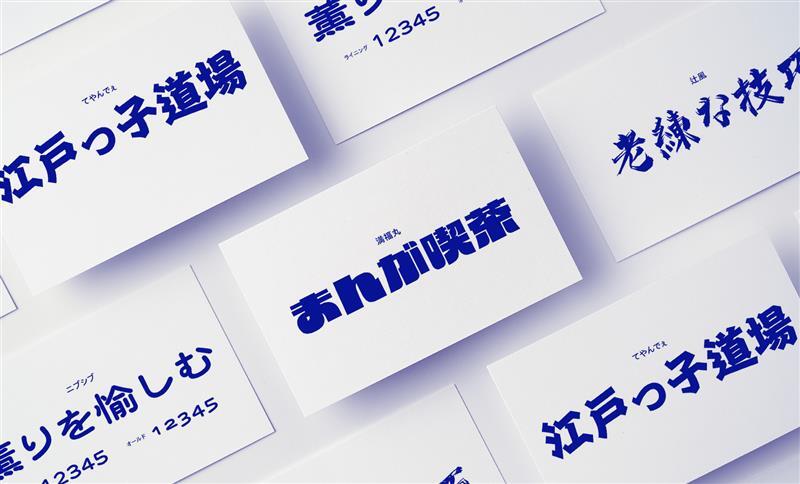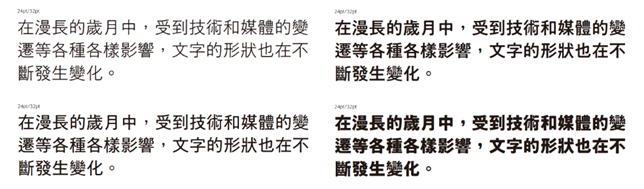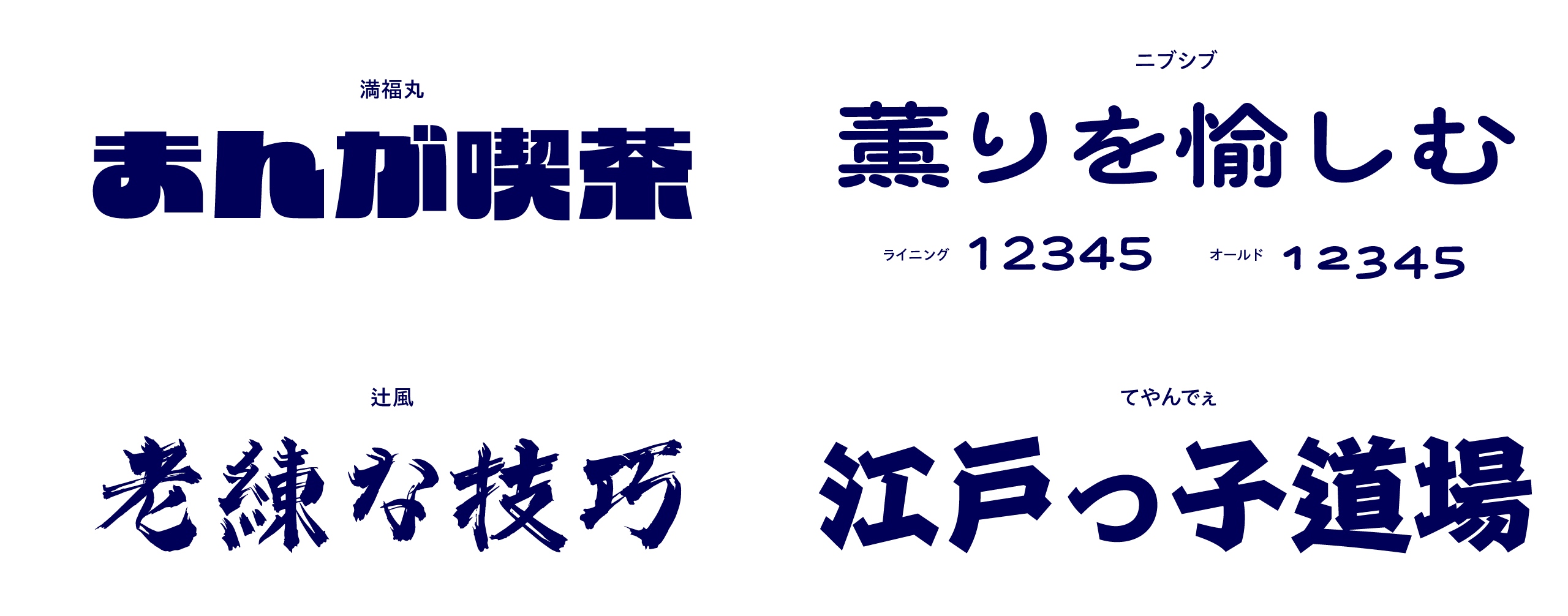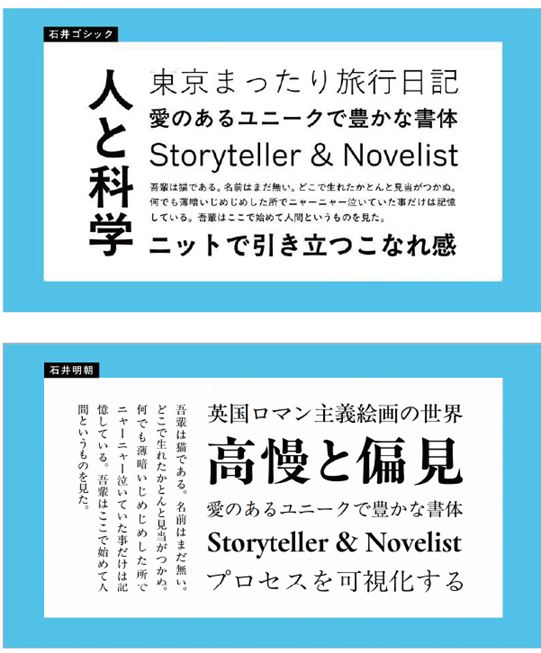
株式會社森澤自2025年10月1日起,於iFontCloud文鼎雲字庫上開始提供10款全新字體家族
株式會社森澤自2025年10月1日起,於iFontCloud文鼎雲字庫上開始提供10款全新字體家族。
此次新增的字體,進一步強化了涵蓋多樣風格、對應廣泛用途的字體陣容。
其中,「A1黑體繁體字」是一款專為繁體中文設計的字體,筆劃交錯處帶有油墨暈染效果與圓角處理,兼具有溫度的設計感與優異的易讀性。
無論用於標題或內文皆十分合適,是一款對應繁體中文、通用性很高的黑體字型
充滿獨特個性,適合用於標題等場合的設計字體也更加豐富了。
包括下半部筆畫具有厚重感、造型獨特的「滿福丸」,
帶有手寫招牌字風格的「ニブシブ (Nibushibu)」,
以書法家的毛筆字為基礎設計的「辻風」,
以及充滿江戶風情的「てやんでぇ (Teyandee)」等字體。
名稱中帶有『石井』的字型,是以對日本平面設計產生重大影響的寫研照相打字機字體為基礎所設計的字型。
包含了依照現代環境重新詮釋的石井明朝、石井黑體,以及帶有照相打字全盛時期設計風格的石井中明朝、石井中黑體、石井中圓體。